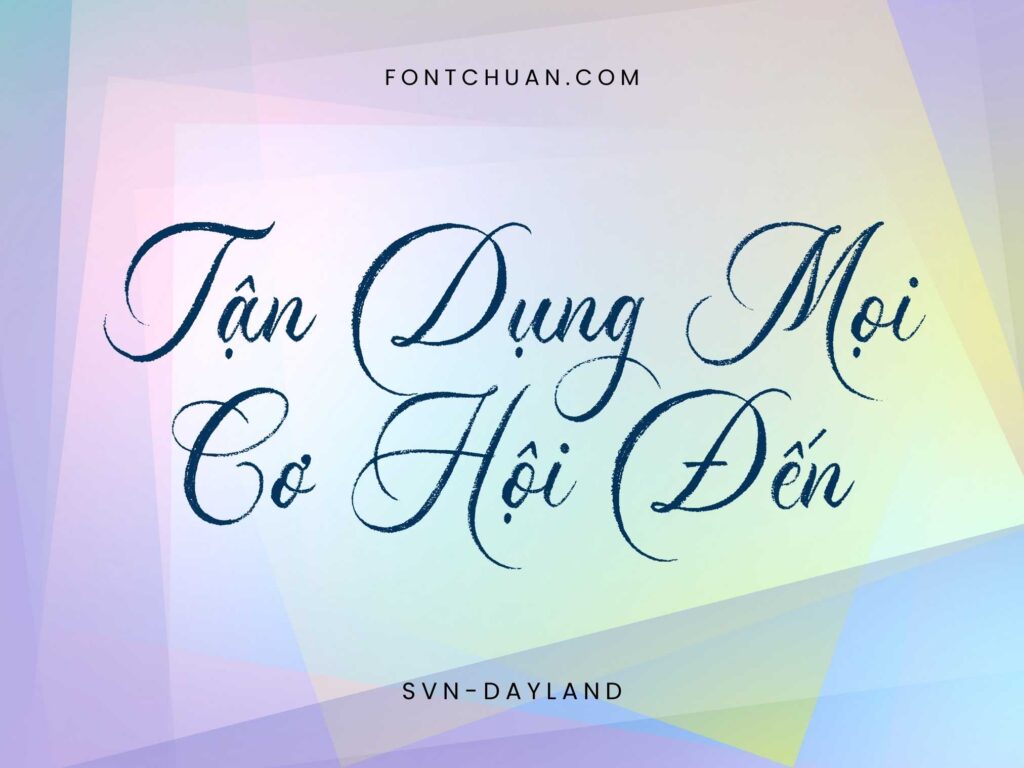
Font SVN Dayland Việt Hóa
Tác giả Font: Blankids Studio
Dayland là một font chữ calligraphy được thiết kế bởi Blankids Studio, mang phong cách viết tay mềm mại và tinh tế. Font này phù hợp cho các thiết kế như logo chữ ký, thiệp mời đám cưới, câu trích dẫn lãng mạn, logotype, poster, bộ công cụ truyền thông xã hội, bìa sách, thiết kế áo thun, bao bì và nhiều hơn nữa. Font đã được Việt hóa để hỗ trợ tiếng Việt bởi STYLEno.1 Fonts, đồng thời hỗ trợ nhiều ngôn ngữ khác, giúp mở rộng phạm vi sử dụng trên toàn cầu. Font này được chia sẻ miễn phí cho mục đích sử dụng cá nhân trên trang STYLEno.1 Fonts, đáp ứng nhu cầu của người dùng và ứng dụng thực tế vào các dự án thiết kế.
Đặc điểm thiết kế của Dayland bao gồm các nét chữ viết tay uyển chuyển và thanh lịch, tạo cảm giác lãng mạn và tinh tế. Font này phù hợp cho các ứng dụng như thiệp mời, tiêu đề, logo, bài đăng trên mạng xã hội, quảng cáo, bao bì sản phẩm và bất kỳ dự án nào cần đến sự tinh tế của chữ viết tay. Các ngành nghề phù hợp bao gồm quảng cáo, nghệ thuật và thiết kế đồ họa.